Việc tìm kiếm và sử dụng font chữ đẹp Tiếng Việt chuẩn mực luôn là một thách thức đối với các nhà thiết kế, content creator hay bất kỳ ai muốn tạo ra tài liệu chuyên nghiệp. Bài viết này, sẽ tổng hợp trọn bộ các font chữ đẹp Tiếng Việt "cần phải có" cho kho tài nguyên của bạn. Chúng tôi sẽ phân loại chi tiết các font dành cho mục đích đánh máy chuyên nghiệp và các font viết tay sáng tạo, đồng thời hướng dẫn chi tiết cách cài đặt để bạn có thể áp dụng ngay lập tức.
Một font chữ kém chất lượng, bị lỗi dấu hoặc thiếu tính thẩm mỹ có thể phá hỏng toàn bộ công sức của một thiết kế, bất kể nội dung đó có giá trị đến đâu.
Việc chọn một font phù hợp thể hiện sự tinh tế, chỉn chu và sự tôn trọng đối với người xem/độc giả. Trong kinh doanh, một font chữ được lựa chọn cẩn thận là nền tảng để xây dựng hình ảnh thương hiệu đáng tin cậy.
Các font được thiết kế tốt (như Roboto, Lato, v.v.) giúp văn bản đạt được mức độ dễ đọc cao, đặc biệt quan trọng trên môi trường kỹ thuật số, nơi người dùng thường xuyên lướt qua nội dung. Font chữ rõ ràng giúp giảm mỏi mắt và tăng khả năng tiếp thu thông tin.
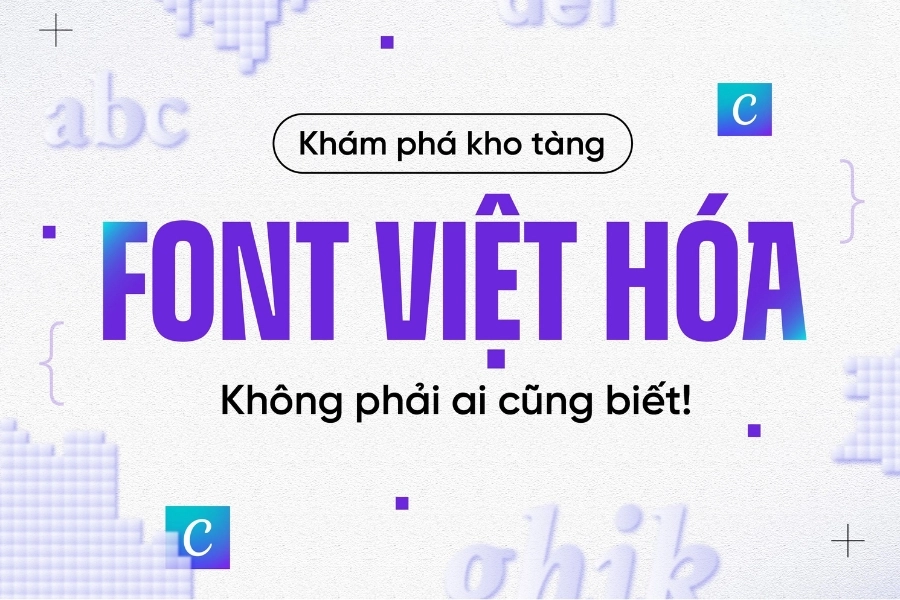
Mỗi font chữ mang một cá tính riêng: cổ điển, hiện đại, tối giản, vui tươi, hay mạnh mẽ. Ví dụ, font Serif thường gợi lên sự sang trọng, truyền thống, trong khi Sans-serif tạo cảm giác hiện đại, công nghệ.
Font chữ phải được Việt hóa chuẩn, đảm bảo không có hiện tượng dấu bị chồng lên nhau hoặc các ký tự đặc biệt bị lỗi (hay còn gọi là lỗi encoding). Việc này không chỉ ảnh hưởng đến tính thẩm mỹ mà còn là sự tôn trọng đối với ngôn ngữ quốc gia.
Nhóm font này lý tưởng cho các nội dung chính, văn bản dài, thiết kế giao diện (UI/UX), báo cáo, và các ấn phẩm cần sự rõ ràng, hiện đại. Chúng chủ yếu thuộc dòng Sans-serif (không chân) hiện đại, tập trung vào tính dễ đọc và thẩm mỹ.
Phong cách tóm lược: Hiện đại, linh hoạt, Sans-serif trung tính.
Mô tả chi tiết: Roboto là một trong những font chữ phổ biến nhất thế giới, được Google phát triển như font chữ mặc định cho hệ điều hành Android. Font có cấu trúc hình học rõ ràng nhưng vẫn giữ được những nét cong thân thiện, tạo nên sự cân bằng hoàn hảo giữa tính kỹ thuật và tính nhân văn. Đây là lựa chọn hàng đầu cho các thiết kế giao diện ứng dụng, website và mọi nội dung cần sự rõ ràng, dễ đọc trên đa nền tảng.
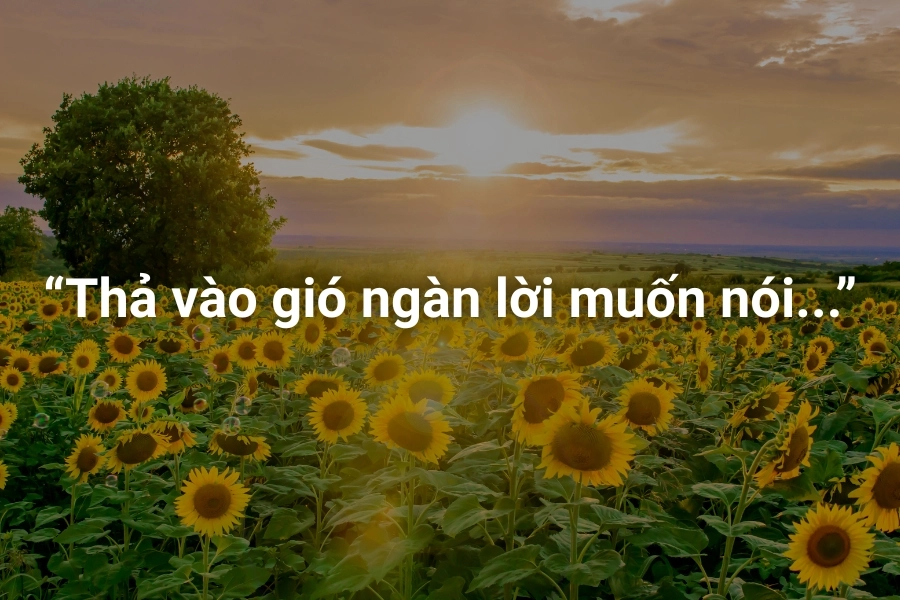
Phong cách tóm lược: Hình học, mạnh mẽ, cá tính.
Mô tả chi tiết: Lấy cảm hứng từ những biển hiệu cổ điển ở khu phố Montserrat (Buenos Aires, Argentina), font chữ này mang tính hình học cao, tạo cảm giác mạnh mẽ, vững chãi và rất "sạch sẽ". Montserrat được ưa chuộng cho các tiêu đề lớn, poster, và header website nhờ vào độ dày dặn và cá tính thương hiệu rõ rệt. Đây là một lựa chọn tuyệt vời khi cần một font thay thế cho Gotham hoặc Proxima Nova.
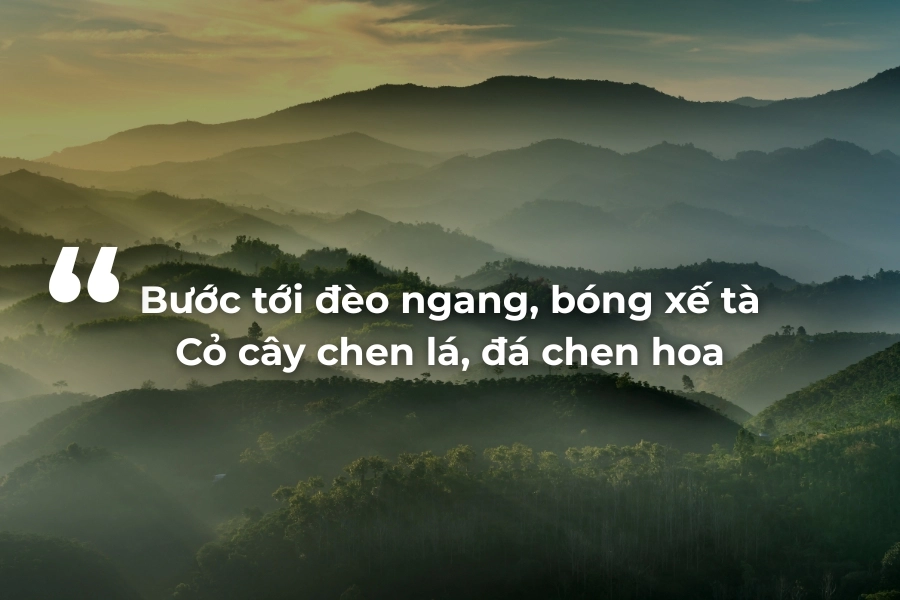
Phong cách tóm lược: Ấn tượng, đậm nét, thu hút.
Mô tả chi tiết: Paytone One là một font chữ đậm (display) được thiết kế để thu hút sự chú ý ngay lập tức. Với các nét chữ to, tròn và đầy đặn, nó là lựa chọn lý tưởng cho các banner quảng cáo, logo hoặc các thông báo cần nhấn mạnh và nổi bật. Font này mang lại cảm giác năng lượng và sự tươi mới.
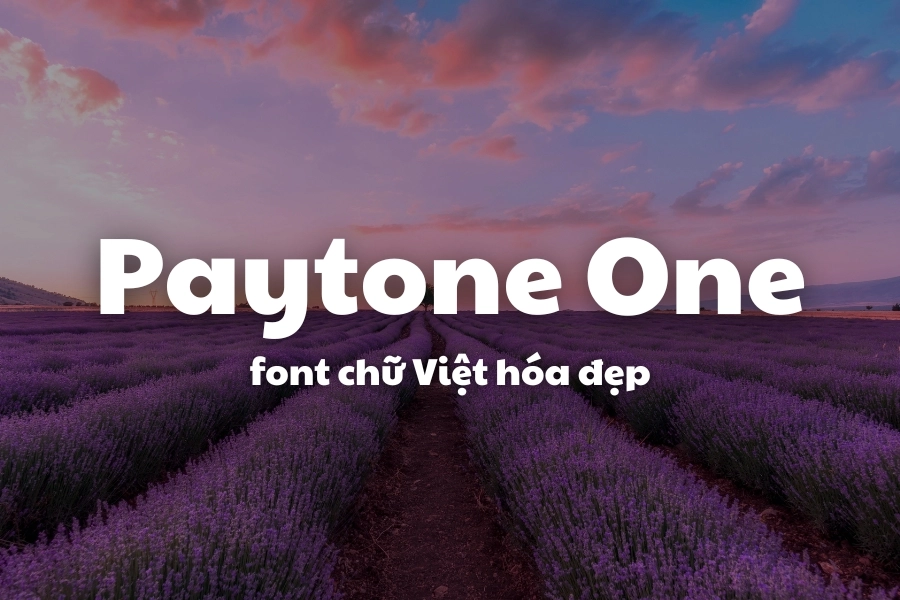
Phong cách tóm lược: Thanh lịch, thân thiện, dễ đọc.
Mô tả chi tiết: Tên gọi "Lato" trong tiếng Ba Lan có nghĩa là "Mùa hè". Font chữ này mang lại cảm giác ấm áp, thân thiện nhờ các nét chữ bán tròn trịa và sự cân đối tinh tế. Với nhiều trọng lượng (weight) khác nhau, Lato rất thích hợp cho nội dung chính, sách điện tử và tài liệu in ấn, nơi cần sự dễ chịu và duyên dáng trong suốt bài đọc dài.
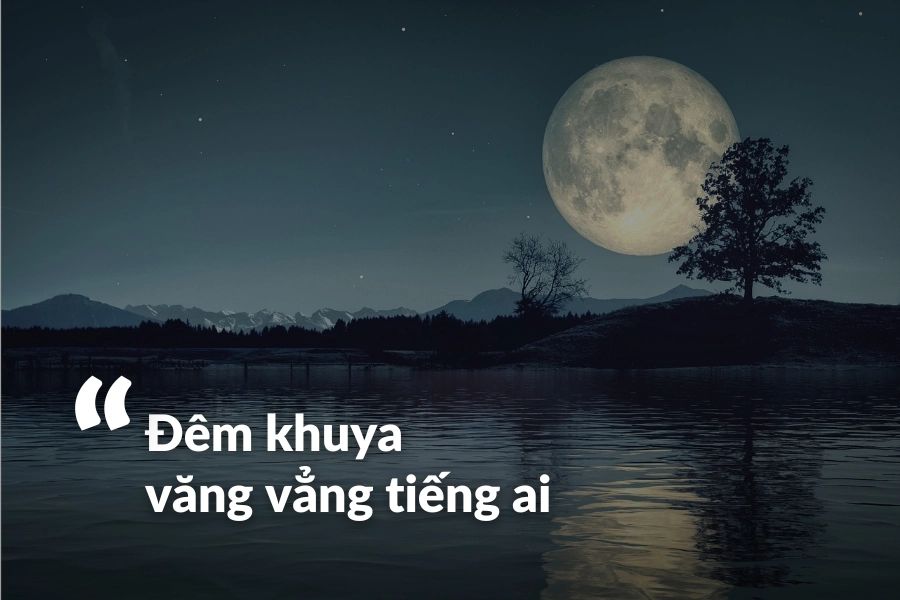
Phong cách tóm lược: Trẻ trung, độc đáo, hơi hướng Display.
Mô tả chi tiết: Phudu là một font hiển thị với nét chữ có sự "nghệ thuật" và độ độc đáo riêng, thoát khỏi những tiêu chuẩn Sans-serif thông thường. Font này rất phù hợp với các dự án thiết kế sáng tạo, cá tính, hoặc bìa sách cần sự phá cách và ấn tượng thị giác mạnh mẽ.
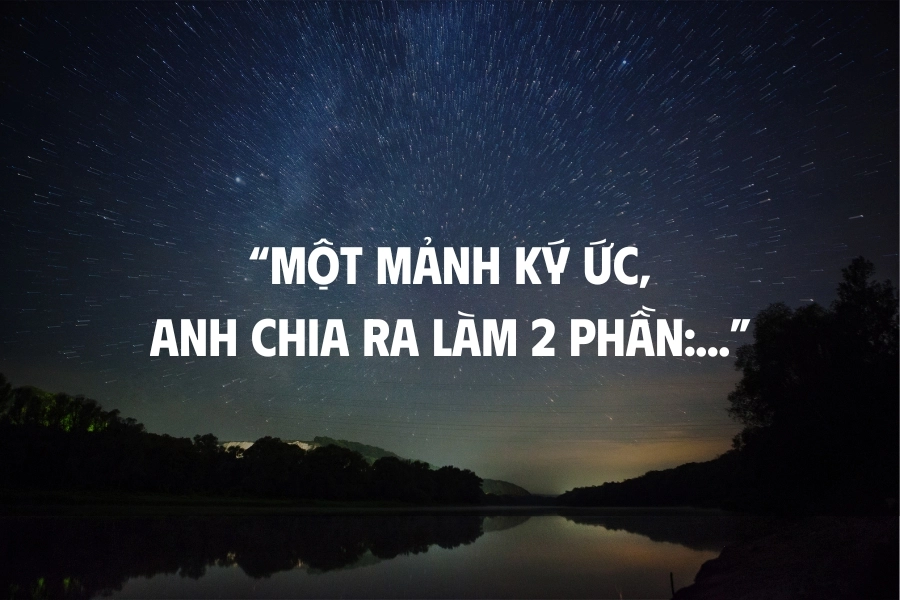
Phong cách tóm lược: Tối giản, sắc nét, cao cấp.
Mô tả chi tiết: Đây là một font chữ Việt hóa mang đặc trưng sắc nét, hiện đại và tối giản, được thiết kế bởi iCiel và mang hơi hướng công nghiệp. Sự gọn gàng và tinh tế của font giúp tạo nên vẻ ngoài chuyên nghiệp và cao cấp, thường được sử dụng trong branding doanh nghiệp lớn hoặc các thiết kế công nghệ.
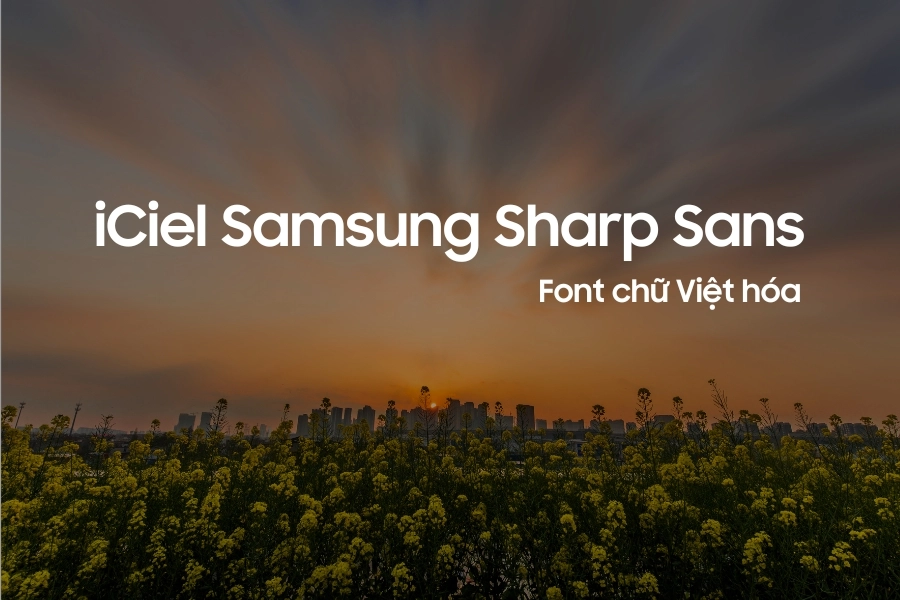
Phong cách tóm lược: Dịu dàng, vui tươi, Script/Display.
Mô tả chi tiết: Sunflora là một font hiển thị có tính thẩm mỹ cao, mang nét mềm mại, dịu dàng, thường được các nhà thiết kế Việt Nam yêu thích. Font chữ này là một lựa chọn tuyệt vời cho các thiết kế liên quan đến thời trang, làm đẹp, thiệp mời, hoặc các ấn phẩm có tính nghệ thuật và cảm xúc cao.
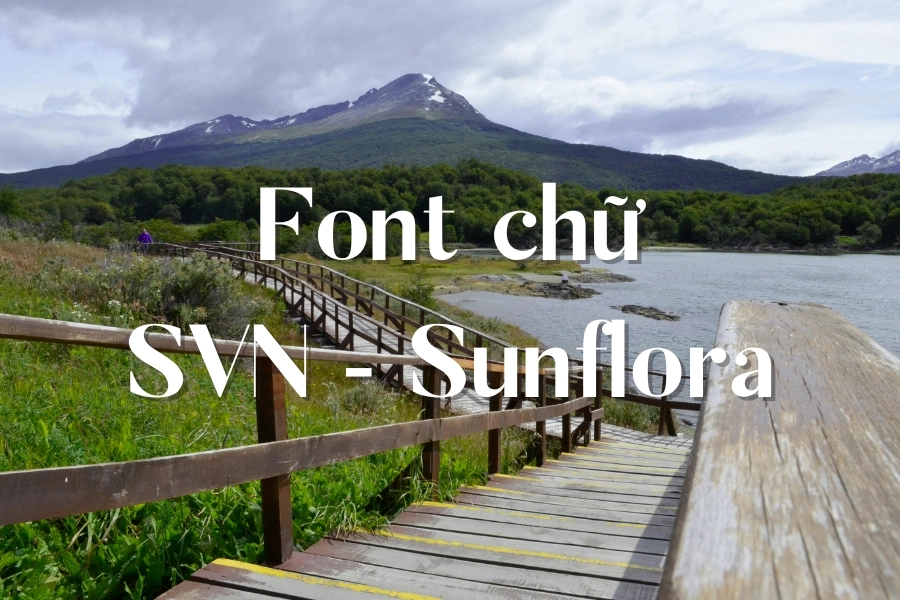
Phong cách tóm lược: Cổ điển, thanh lịch, Serif.
Mô tả chi tiết: Là một font có chân (Serif) với nét cổ điển và sang trọng, Ranoya gợi nhớ đến phong cách của các tạp chí in ấn lâu đời. Font này thường được sử dụng cho logo, tiêu đề tạp chí hoặc các ấn phẩm yêu cầu sự trang trọng, lịch thiệp và mang tính học thuật cao.
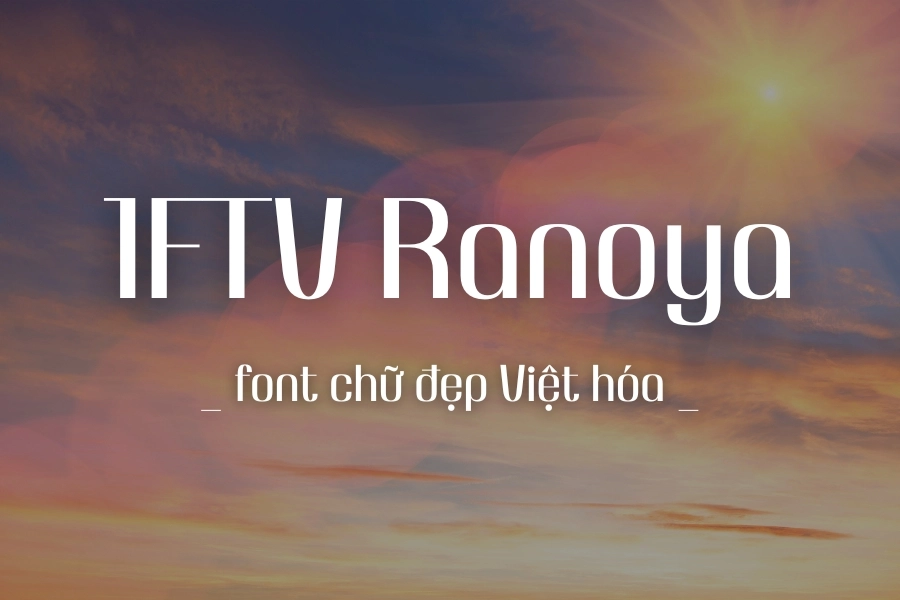
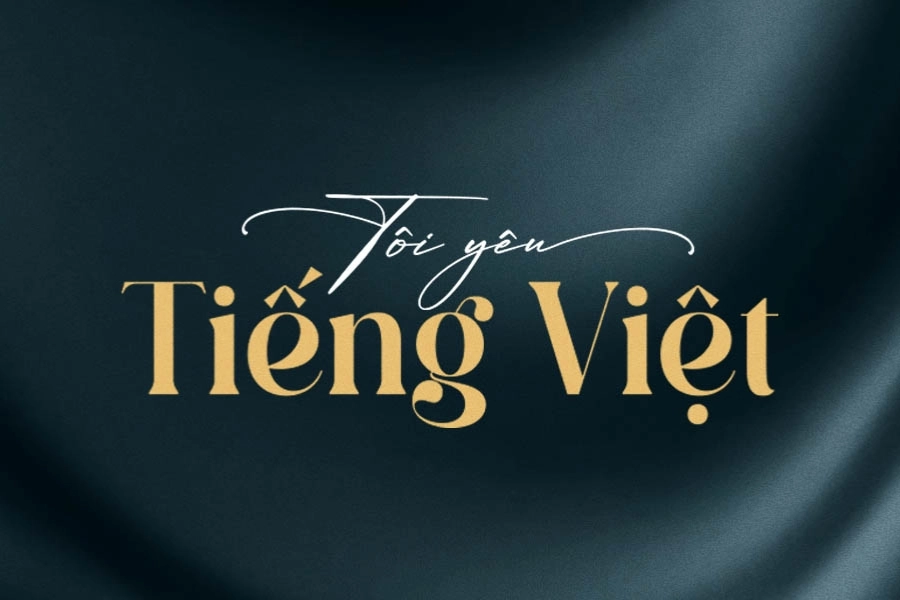
Với danh sách tổng hợp chi tiết và phân loại rõ ràng các font đánh máy chuyên nghiệp và font viết tay sáng tạo này, cùng với hướng dẫn cài đặt chi tiết, hy vọng bạn đã có thể bổ sung những công cụ đắc lực nhất vào kho tài nguyên của mình. Hãy mạnh dạn thử nghiệm các phong cách font khác nhau để tìm ra "ngôn ngữ" thị giác hoàn hảo nhất, nâng tầm các sản phẩm thiết kế và nội dung của bạn ngay hôm nay!